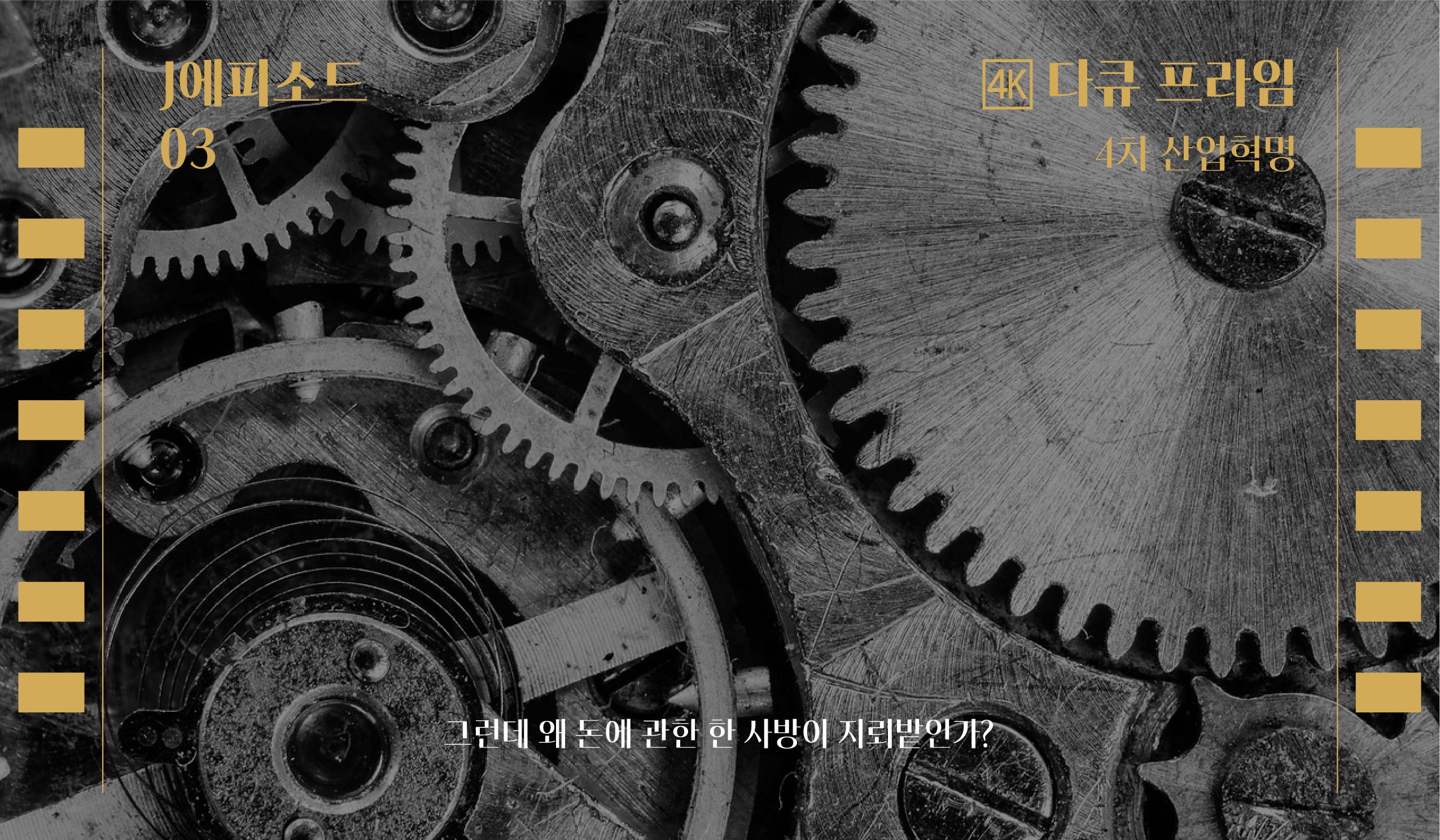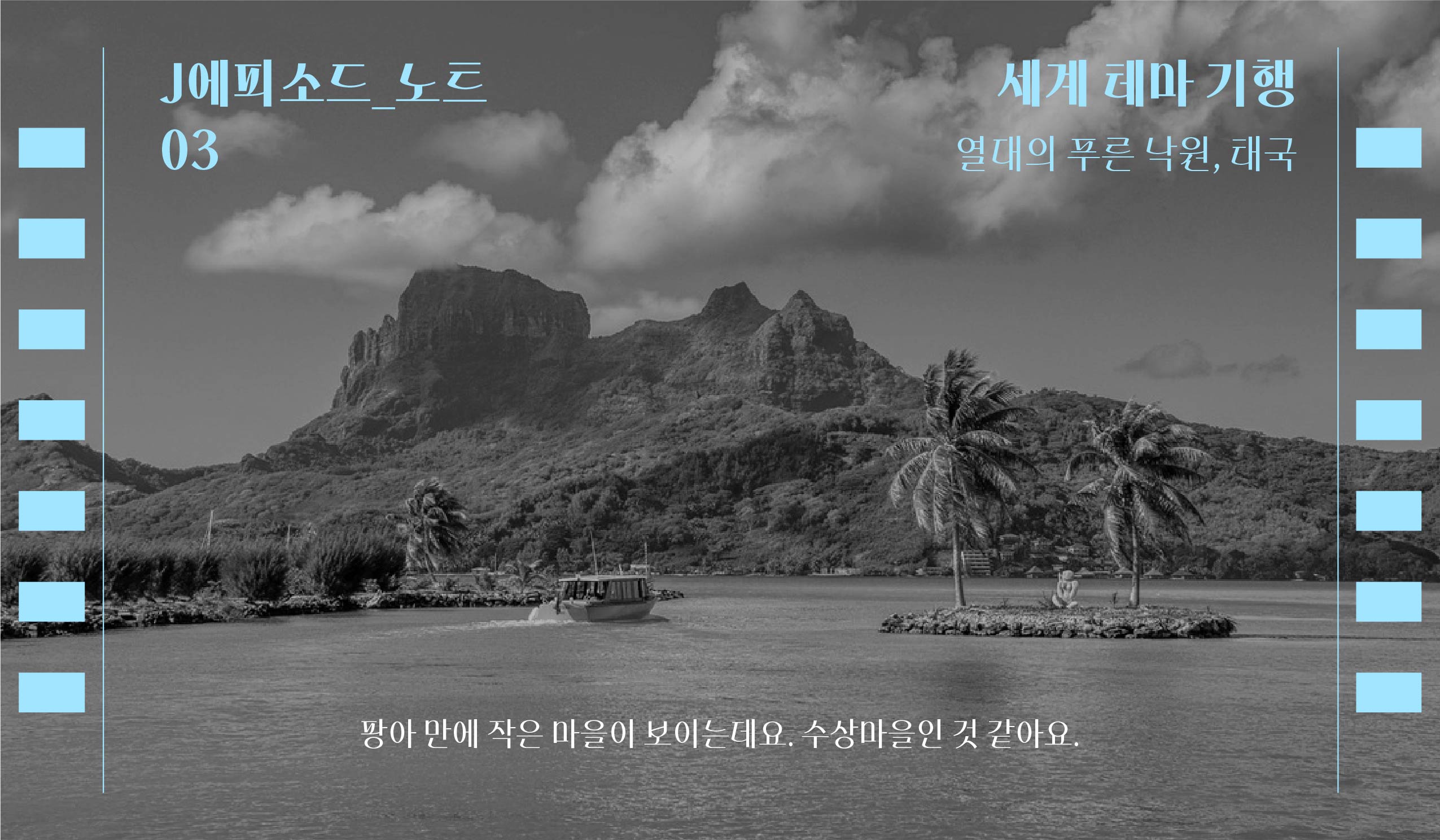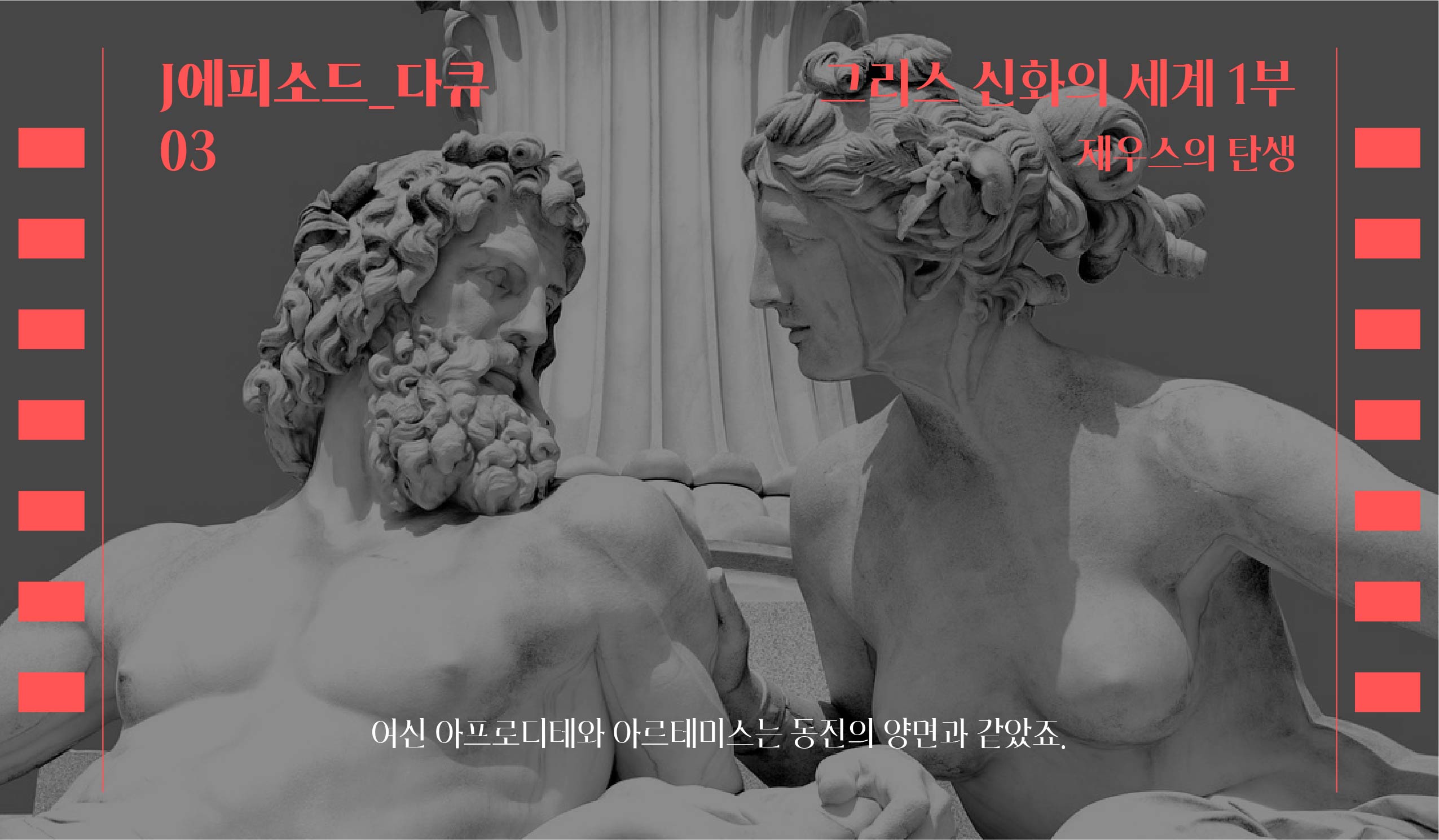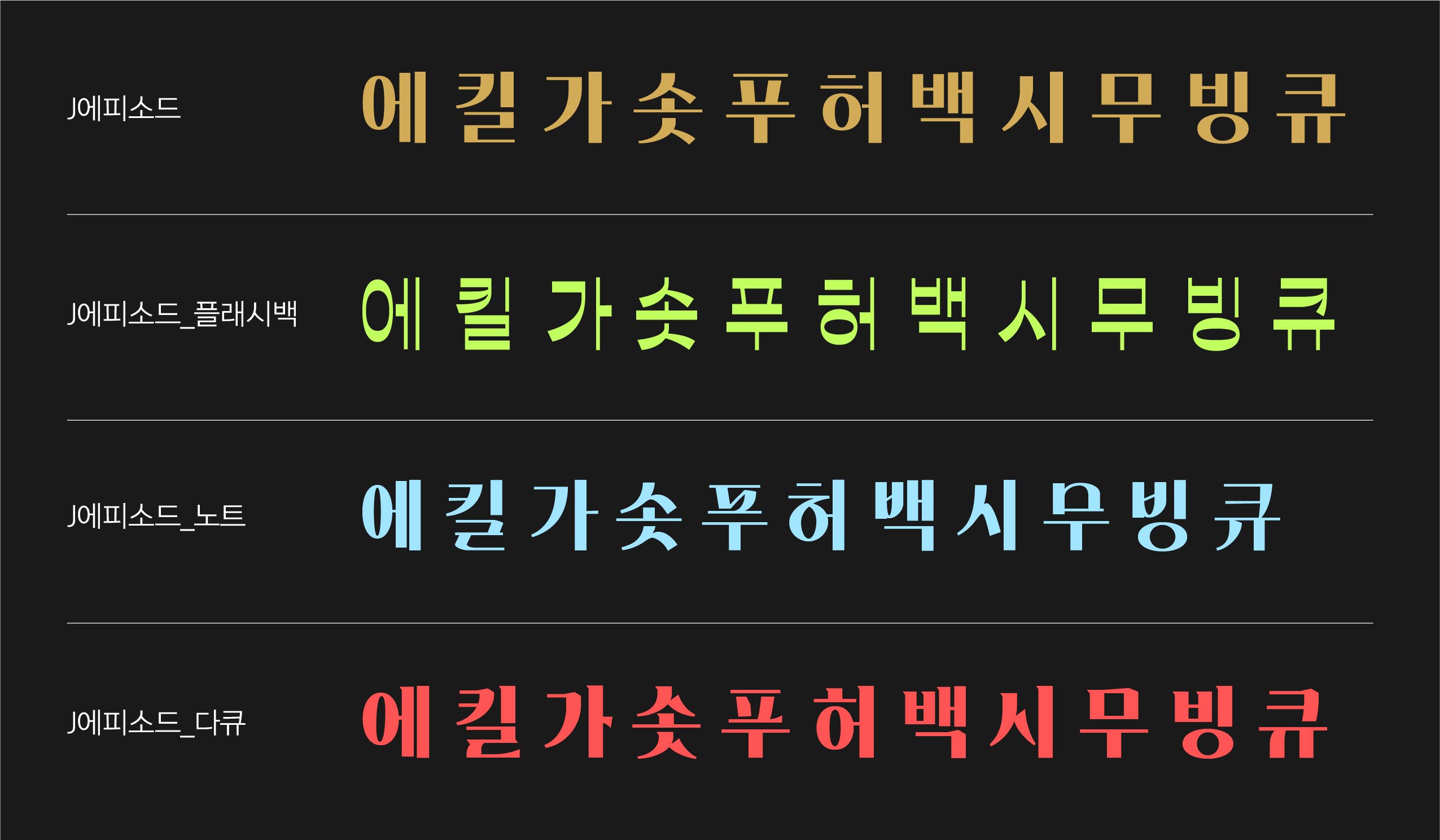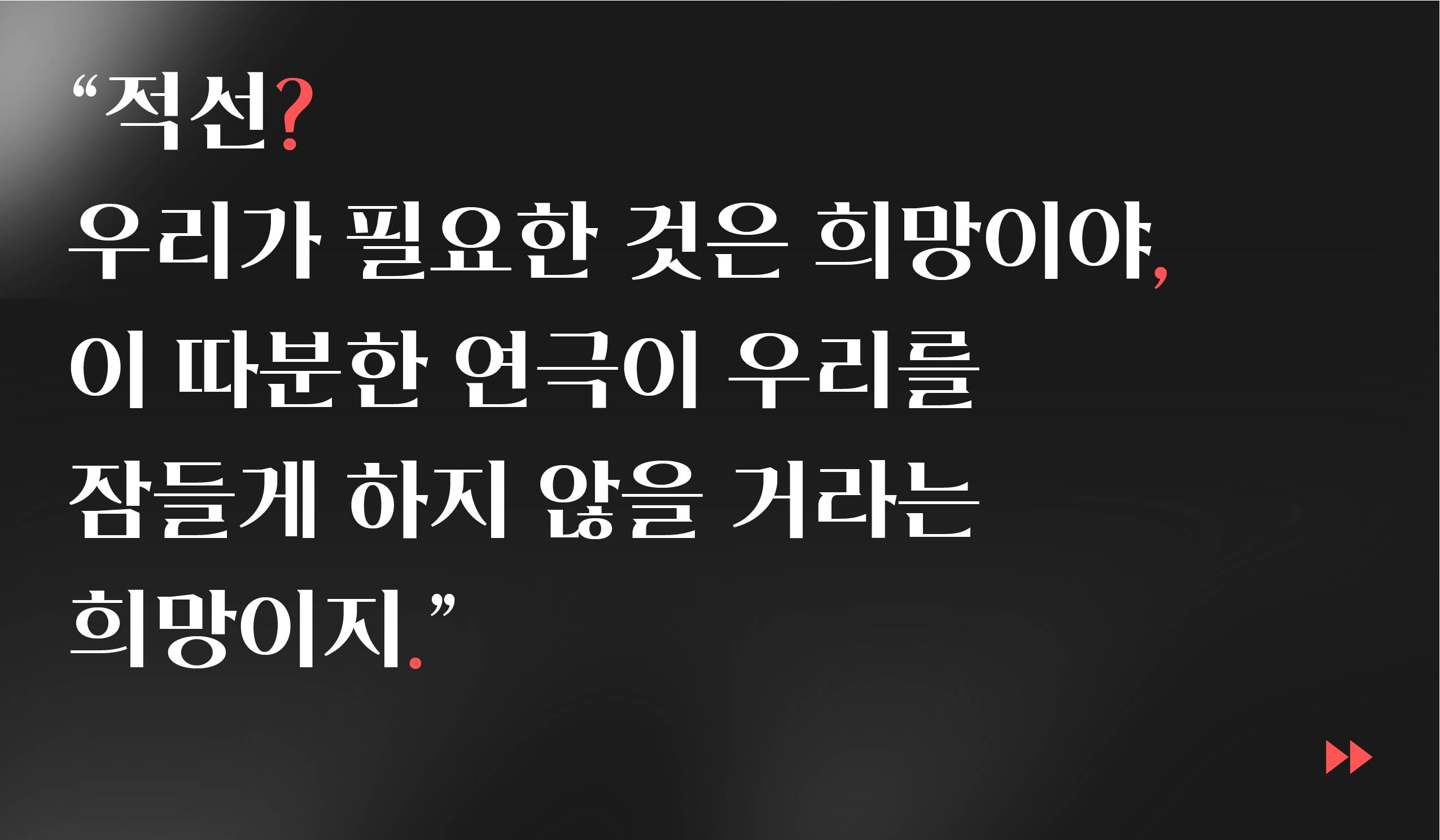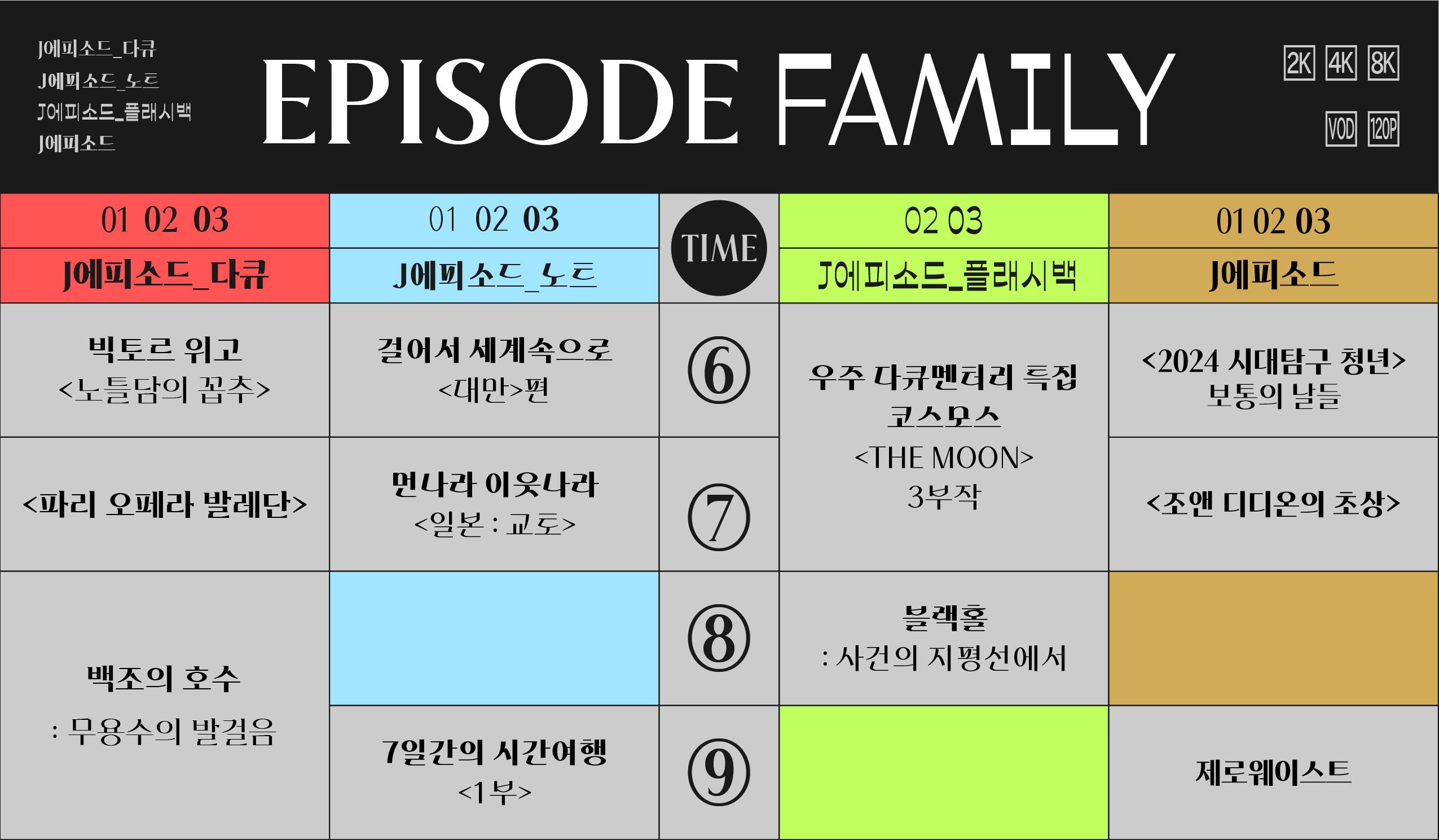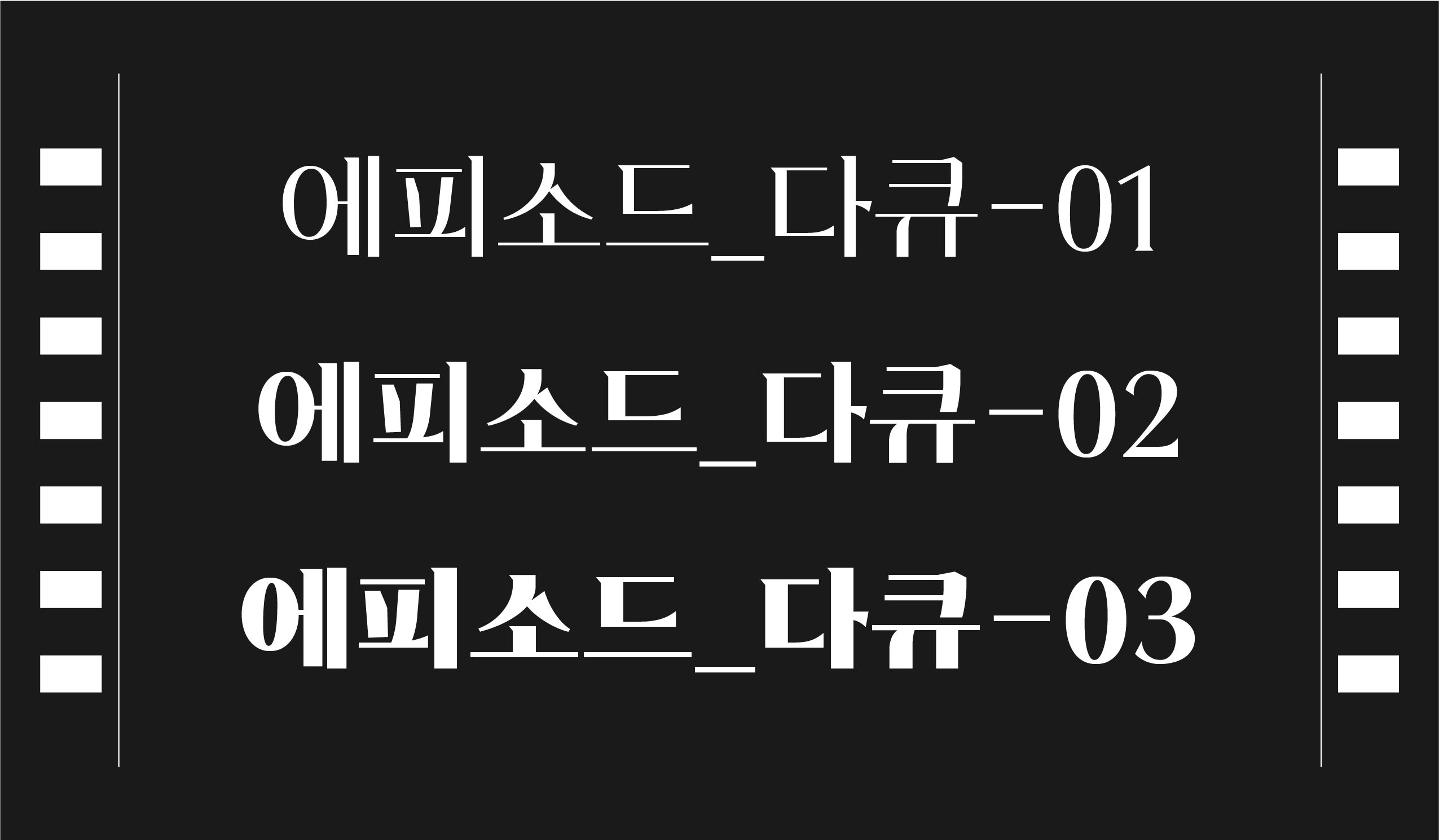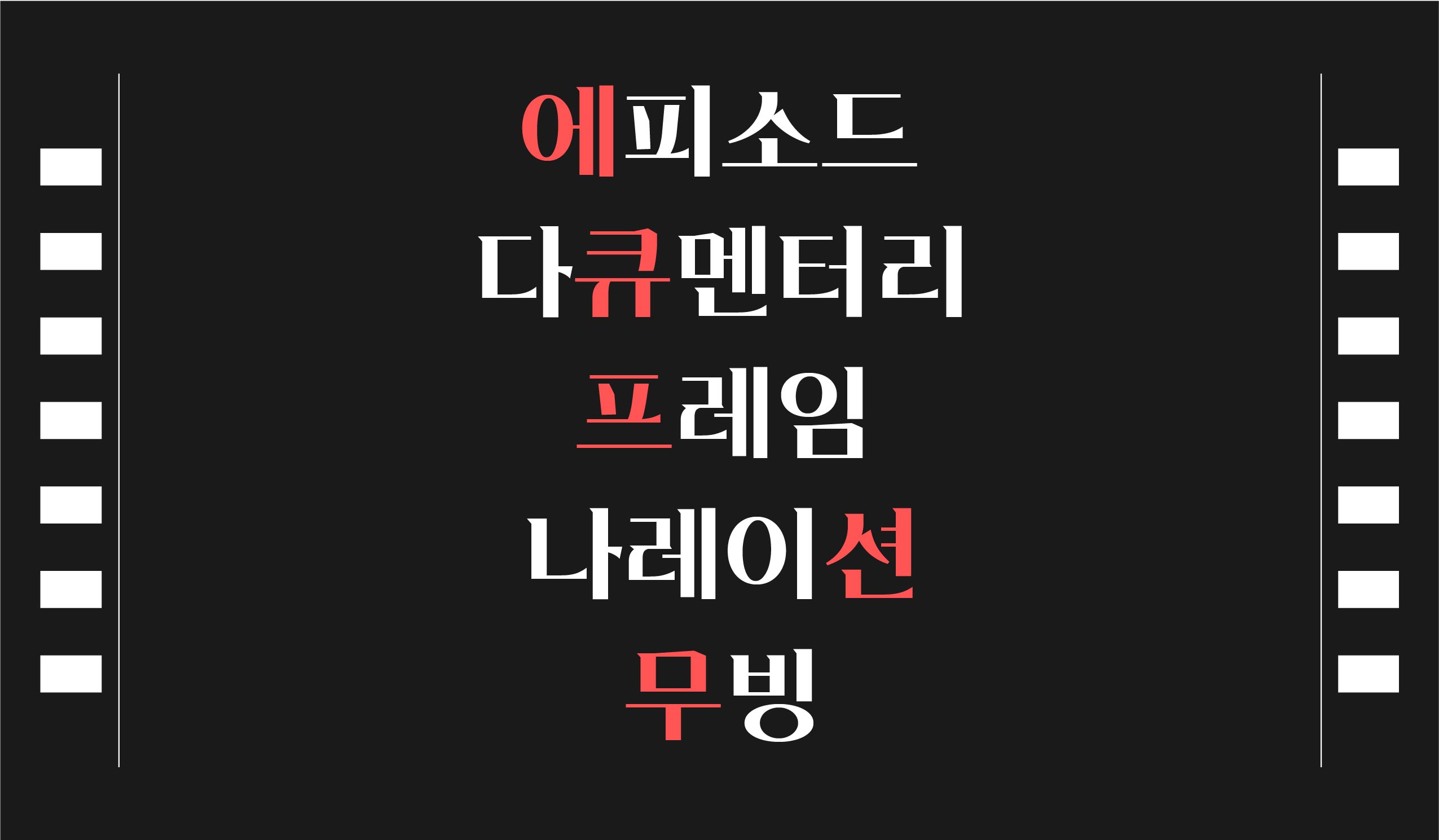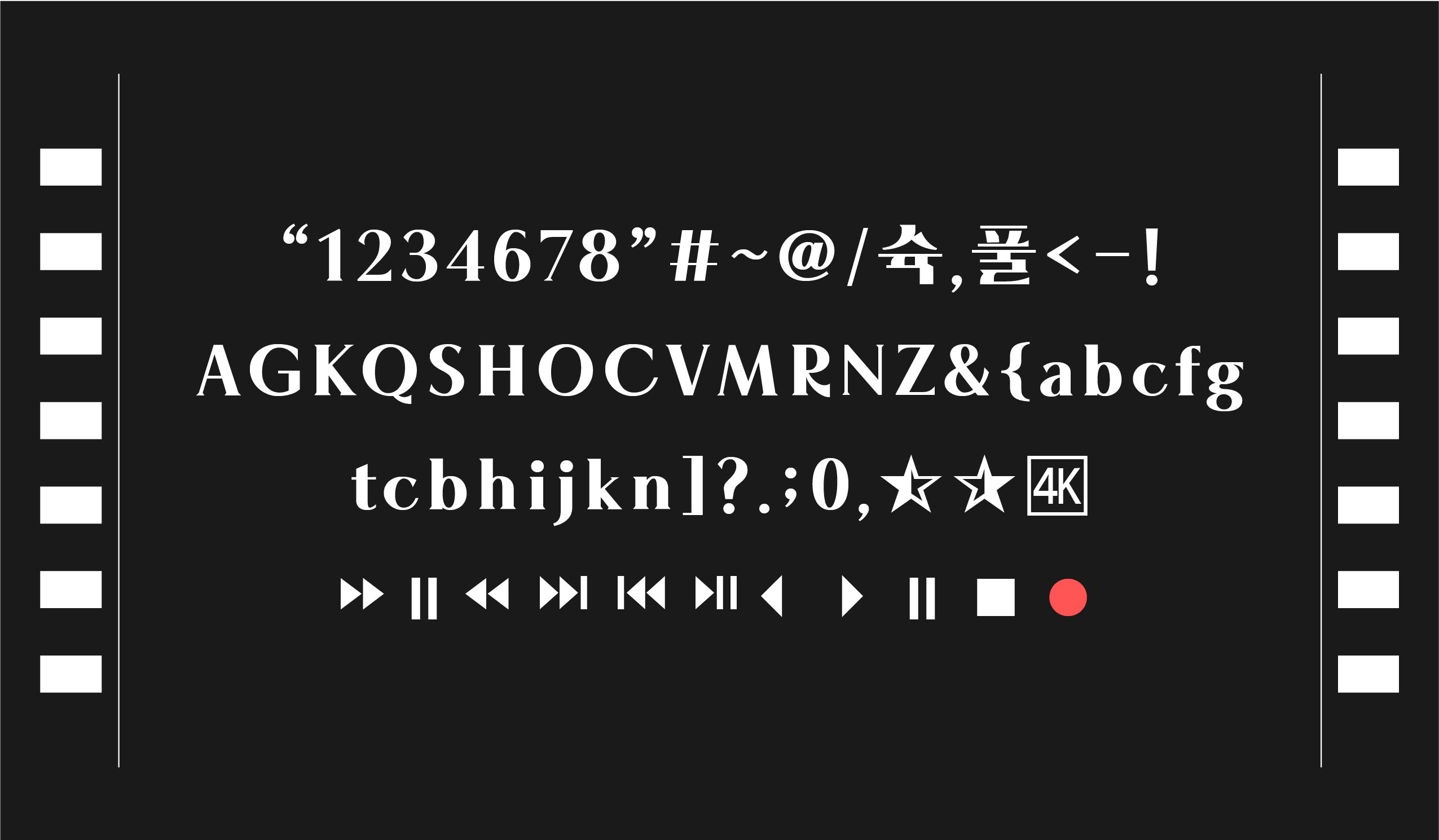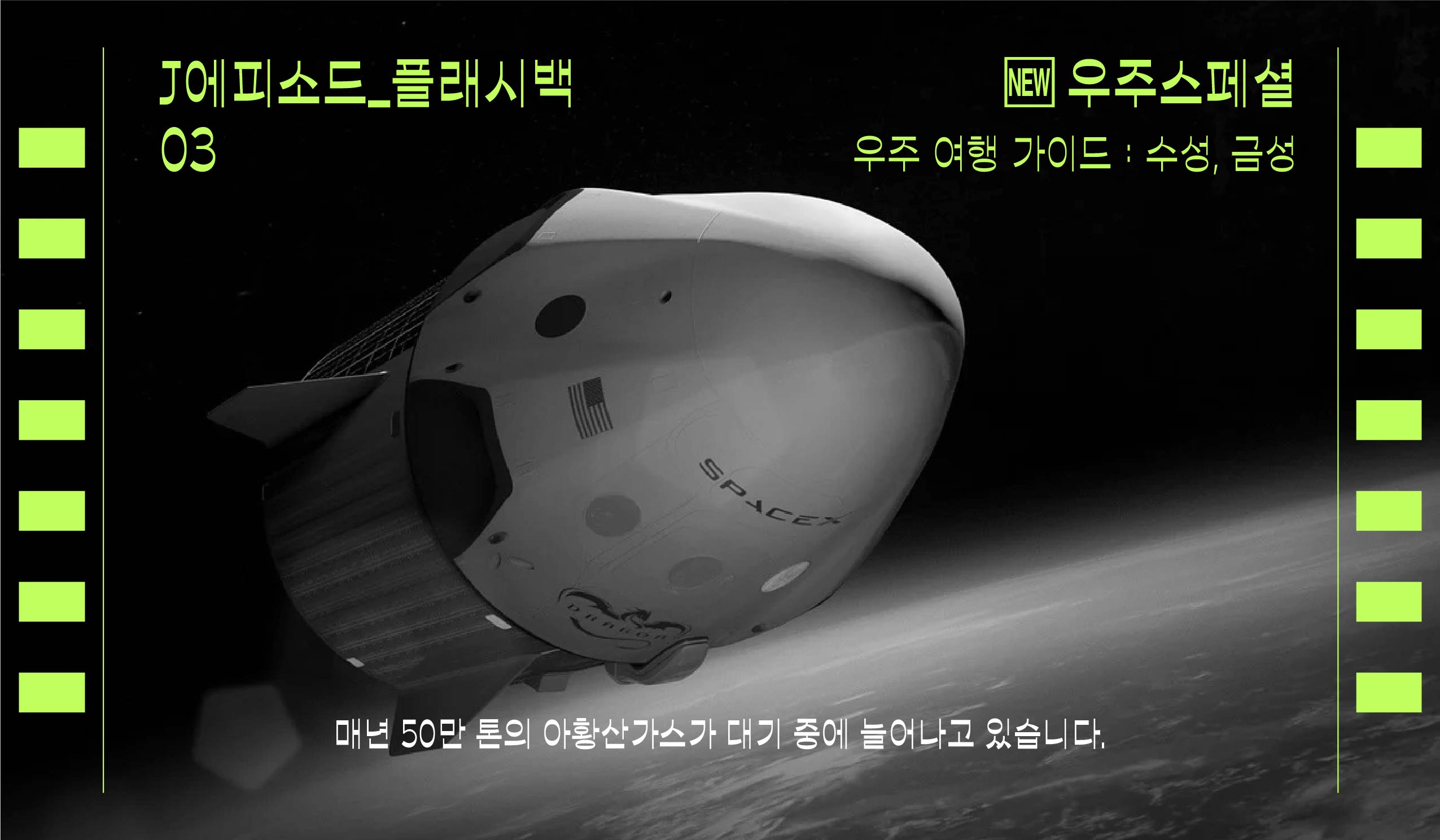
다양한 컨셉으로 활용이 가능하고 독특한 디자인 요소가 많은 서체 시리즈. 개성있는 디테일로 시각적 재미를 더하고 풍부한 이야기를 담을 수 있는 서체이다.
에피소드 패밀리는 “획 대비” 와 “그래픽체”로서 다양한 시도를 보여주고 있으며 에피소드_다큐까지 포함하여 총 11종으로 구성되어 있습니다.
에피소드_다큐는 이미 출시된 에피소드 패밀리와는 다르게 세리프가 더해진 디자인으로 기획되었으며 다큐멘터리라는 이름에 걸맞는 진지함과 에피소드 패밀리가 가지는 우아함을 표현하고자 했습니다. 이응 형태의 기울기, 획의 설계, 세리프의 크기 그리고 곁줄기의 형태에 대한 연구를 통해 표현하였습니다.
01,02,03 총 3종 굵기로 구성되었으며 굵기별 뚜렷한 개성이 돋보입니다.